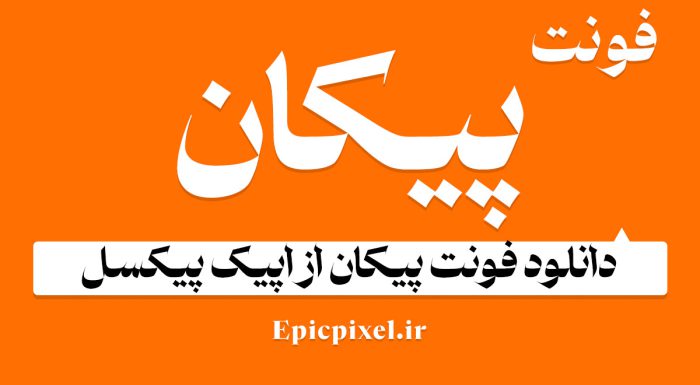
| ⭐ توضیحات | مجموعه ای کامل از فونت های پیکان و نسخه شبیه سازی شده بنام اپیک پیکان
فونت اپیک پیکان با پشتیبانی از حروف فارسی ، انگلیسی / لاتین ، اعداد فارسی Fu Num بهمراه نسخه متغییر Variable و نسخه وب |
با فونت پیکان، در دنیای طراحی بدرخشید!
فونت همیشه یکی از عناصر کلیدی در دنیای طراحی گرافیک بوده است. انتخاب فونت مناسب میتواند پیام شما را به شکلی قدرتمند منتقل کند، توجه مخاطبان را جلب نماید و به برند شما شخصیتی ماندگار ببخشد. در میان انبوه فونتهای موجود، فونت پیکان با ویژگیهای منحصر به فرد خود، گزینهای جسورانه و تاثیرگذار برای طراحان به شمار میرود.
فونت پیکان چیست؟
فونت پیکان، فونتی با الهام از خط نسخ است که با خطوط شکسته و زاویهدار خود، حس قدرت، جدیت و لوکس بودن را القا میکند. نام این فونت نیز با الهام از خودروی محبوب پیکان، یادآور اصالت و نوستالژی است.
ویژگیهای برجسته فونت پیکان
جسورانه و خاص: فونت پیکان با طراحی منحصر به فرد خود، به راحتی از میان سایر فونتها متمایز میشود. این ویژگی باعث میشود تا توجه مخاطبان را در نگاه اول جلب کند و به آنها حس کنجکاوی و هیجان القا نماید.
قابل خواندن: با وجود طراحی خاص، فونت پیکان همچنان خوانایی خود را حفظ کرده است. این امر باعث میشود تا پیام شما به شکلی واضح و موثر به مخاطبان منتقل شود.
مناسب برای تیترها و عناوین: با توجه به ماهیت جسورانهی خود، فونت پیکان بهترین گزینه برای استفاده در تیترها، عناوین و سرصفحهها است. این فونت میتواند به برجستهسازی عناوین شما و جلب توجه مخاطبان کمک شایانی کند.
ایجاد حس لوکس بودن: خطوط صاف و شکستهی فونت پیکان، حس لوکس بودن و خاص بودن را القا میکند. به همین دلیل، این فونت برای برندهای لوکس، محصولات باکیفیت و کمپینهای تبلیغاتی خاص، گزینهای ایدهآل است.
کاربردهای فونت پیکان
همانطور که اشاره شد، فونت پیکان به دلیل ماهیت خاص خود، برای استفاده در موارد زیر مناسب است:
طراحی لوگو و برندینگ: با استفاده از فونت پیکان، میتوانید لوگویی خاص و به یادماندنی برای برند خود خلق کنید.
طراحی پوستر و بروشور: این فونت برای طراحی پوسترهای تبلیغاتی، بروشورهای اطلاعرسانی و سایر اقلام چاپی که نیازمند جلب توجه مخاطبان هستند، بسیار مناسب است.
طراحی وبسایت: با استفاده از فونت پیکان در بخشهایی مانند تیترها و عناوین وبسایت خود، میتوانید توجه بازدیدکنندگان را به خود جلب کنید و حس خوشایندی برای آنها ایجاد نمایید.
صنایع مختلف: طراحان در صنایع مختلف مانند مد، فشن، خودروهای لوکس و جواهرات نیز میتوانند از فونت پیکان برای ایجاد حس لوکس بودن و خاص بودن در محصولات و تبلیغات خود استفاده کنند.
نکاتی برای استفاده از فونت پیکان
استفاده به جا: به دلیل ماهیت خاص فونت پیکان، بهتر است از آن به صورت محدود و در بخشهای کلیدی استفاده شود. استفاده بیش از حد از این فونت میتواند خوانایی متن را کاهش دهد و از تاثیرگذاری آن بکاهد.
ترکیب با فونتهای دیگر: برای بهبود خوانایی متن، میتوانید فونت پیکان را با فونتهای سادهتر ترکیب کنید.
توجه به فواصل حروف: فونت پیکان دارای خطوط شکستهای است که ممکن است فاصلهی حروف را تحت تاثیر قرار دهد. بنابراین، هنگام استفاده از این فونت، به تنظیمات فواصل حروف توجه ویژهای داشته باشید.
فونت یکان: این فونت نیز با طراحی مدرن و هندسی خود، گزینهای مناسب برای طراحان خلاق است. فونت یکان در دو خانوادهی تایپفیس نسخ و تحریری ارائه شده است و تنوع وزنی بالایی دارد.
فونت وزیر: فونت وزیر با الهام از خط نستعلیق طراحی شده است و حسی از اصالت و ظرافت را به طرحهای شما میبخشد. این فونت در دو خانوادهی تایپفیس نسخ و تحریری ارائه شده است و تنوع وزنی بالایی دارد.
فونت میترا: این فونت با طراحی ساده و خوانا، برای استفاده در متنهای طولانی مناسب است. فونت میترا در دو خانوادهی تایپفیس نسخ و تحریری ارائه شده است و تنوع وزنی بالایی دارد.
فونت نازنین: این فونت با طراحی فانتزی و ظریف خود، برای استفاده در عناوین و تیترها مناسب است. فونت نازنین در دو خانوادهی تایپفیس نسخ و تحریری ارائه شده است و تنوع وزنی بالایی دارد.
دانلودانتخاب فونت مناسب به عوامل مختلفی مانند نوع پروژه، مخاطبان و سلیقهی طراح بستگی دارد. فونت پیکان با ویژگیهای منحصر به فرد خود، گزینهای ایدهآل برای طراحانی است که به دنبال ایجاد ظاهری خاص و لوکس در پروژههای خود هستند.
نکاتی برای انتخاب فونت
خوانایی: فونت انتخابی شما باید به راحتی خوانده شود.
مناسبت: فونت باید با نوع پروژه و مخاطبان شما همخوانی داشته باشد.
تنوع: فونت انتخابی شما باید تنوع وزنی و ظاهری کافی برای استفاده در بخشهای مختلف پروژه را داشته باشد.
جمعبندی
فونت پیکان با طراحی جسورانه و منحصر به فرد خود، گزینهای ایدهآل برای طراحانی است که به دنبال ایجاد ظاهری خاص و لوکس در پروژههای خود هستند. این فونت با وجود خوانایی، به دلیل خطوط شکسته و زاویهدار خود، حس قدرت، جدیت و نوستالژی را القا میکند.